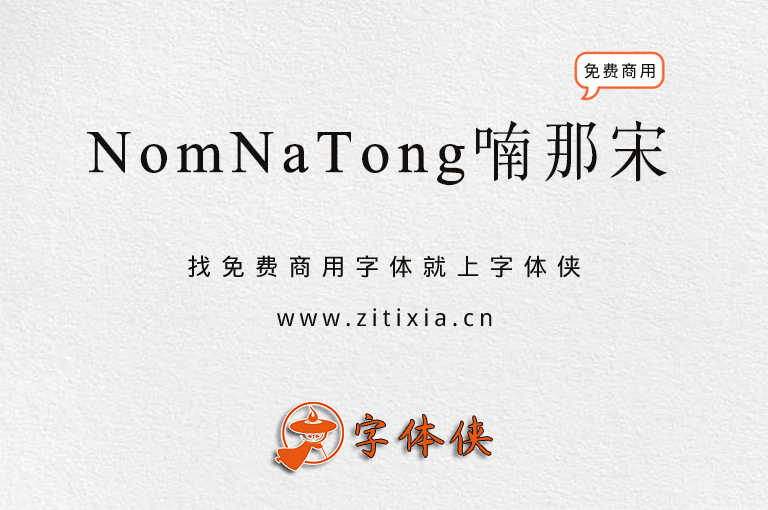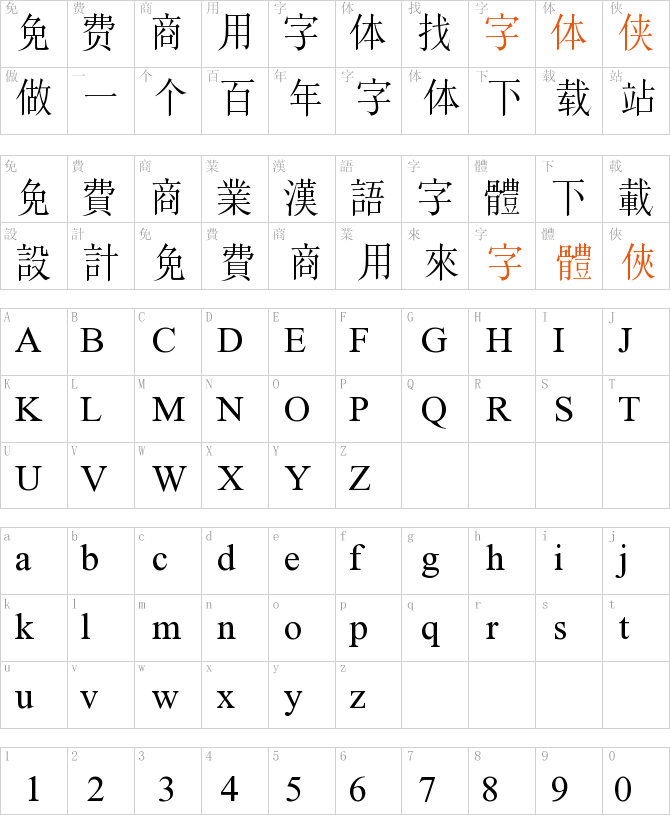
这是“Nom Na Tong”字体的存储库。Nom Na Tong字体最初是在越南Nôm保护基金会的赞助下开发的http://www.nomfoundation.org,成立于1999年。该字体的开发既是以Unicode编码越南Hán-nôm文字的建议的最终来源,也是促进使用该文字书写的作品遗产的途径。该字体目前包含26000多个字形,代表了学者、软件工程师和其他专家的集体工作。它仍然是正在进行的Unicode编码Hán-nôm工作的参考字体。该基金会于2018年底解散。现在,该字体是作为一个开源项目提供的,希望对保存Hán-nôm脚本感兴趣的社区能够继续维护和扩展它。
这三种字体的内容是相同的,但我们在前两种字体中将Postscript名称更改为“NomNaTong Regular”。展望未来,我们鼓励使用NomNaTong Regular,它遵循更传统的字体命名方案。